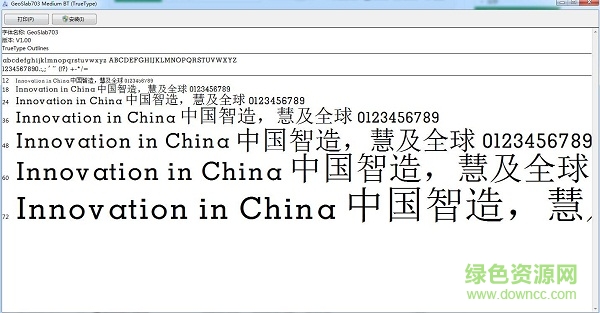
geometricslab703bt medium字體是一款粗細(xì)勻稱(chēng)的英文字體,字型穩(wěn)重,轉(zhuǎn)折處線條優(yōu)干凈利落,極富商業(yè)氣息,可以用在宣傳手冊(cè)、電子閱讀器、海報(bào)設(shè)計(jì)等方面,需要的朋友快來(lái)下載吧!